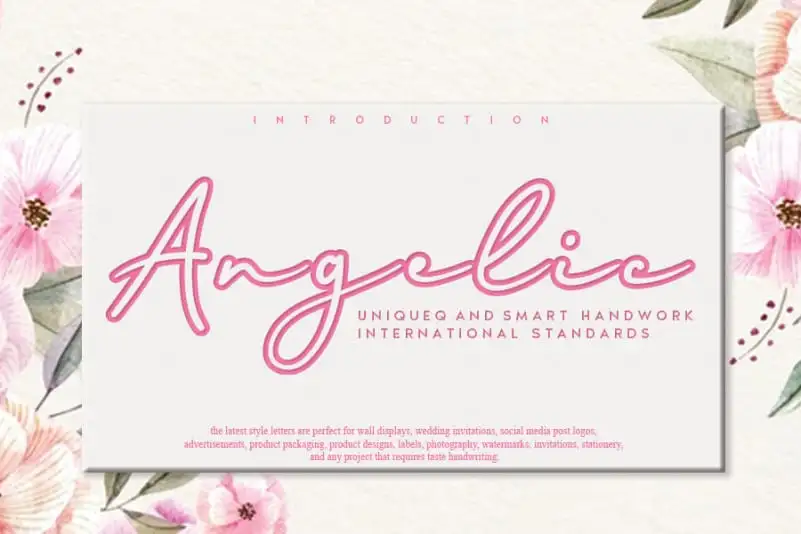
Angelic Script Font – Download Grátis
A Angelic Script Font é inspirada na tipografia clássica, trazendo sua própria estética única a qualquer projeto de design. Seja para as postagens do Instagram ou projetos de caligrafia artesanal, a Angelic faz com que qualquer ideia criativa se torne uma verdadeira obra de arte! Esta fonte é perfeita para quem busca personalidade em seus designs e deseja dar um toque especial à sua produção gráfica. Se você está procurando por uma fonte de escrita artística para adicionar charme a qualquer projeto, a Angelic Script Font é a escolha certa.